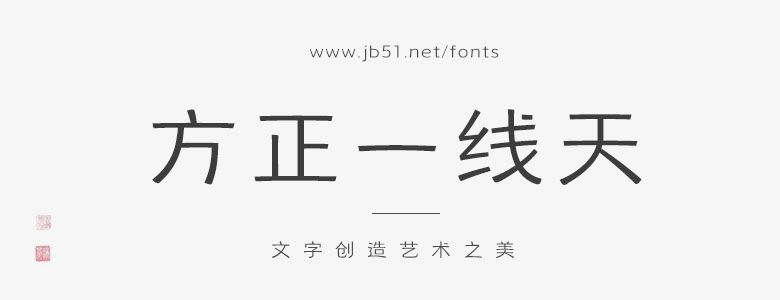
方正一線天從隸書(古典)中來,到黑體(現(xiàn)代)中去,通過澀行與逆勢的表達,極粗與極細的強烈對比來突顯力量與厚重,工穩(wěn)與人文的活字屬性。 在創(chuàng)作之初,作者通過多次書寫來尋找書法與字體的交融點,細心塑造“書法基因”做到既有傳統(tǒng)隸書的法度又不會過于古板張揚,既有黑體的中性統(tǒng)一又不會過于生硬冷俊。放大使用細節(jié)豐富,縮小使用時肌理統(tǒng)一。它的氣質(zhì)是現(xiàn)代的,穩(wěn)重的,自信的,細膩的,實力的,有根可循的人文中性表達。并由此衍生出家族字體,豐富從正文到標題的用字需要。